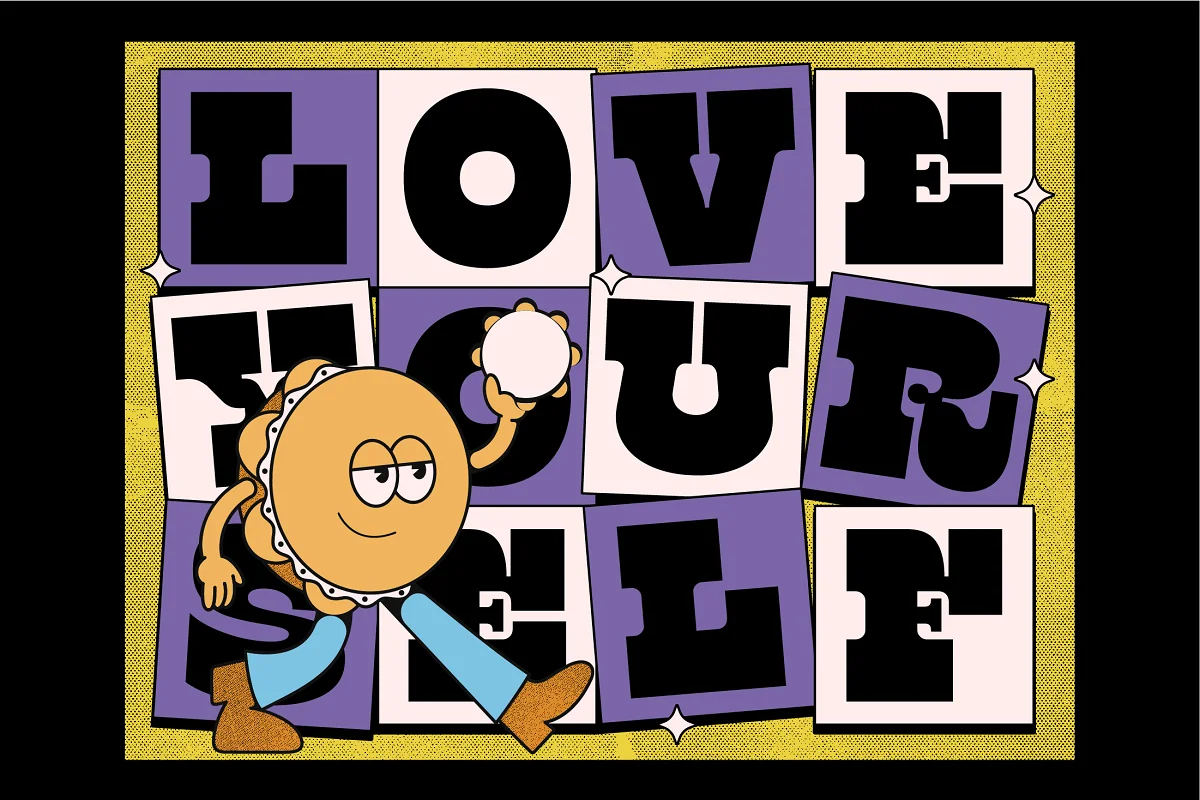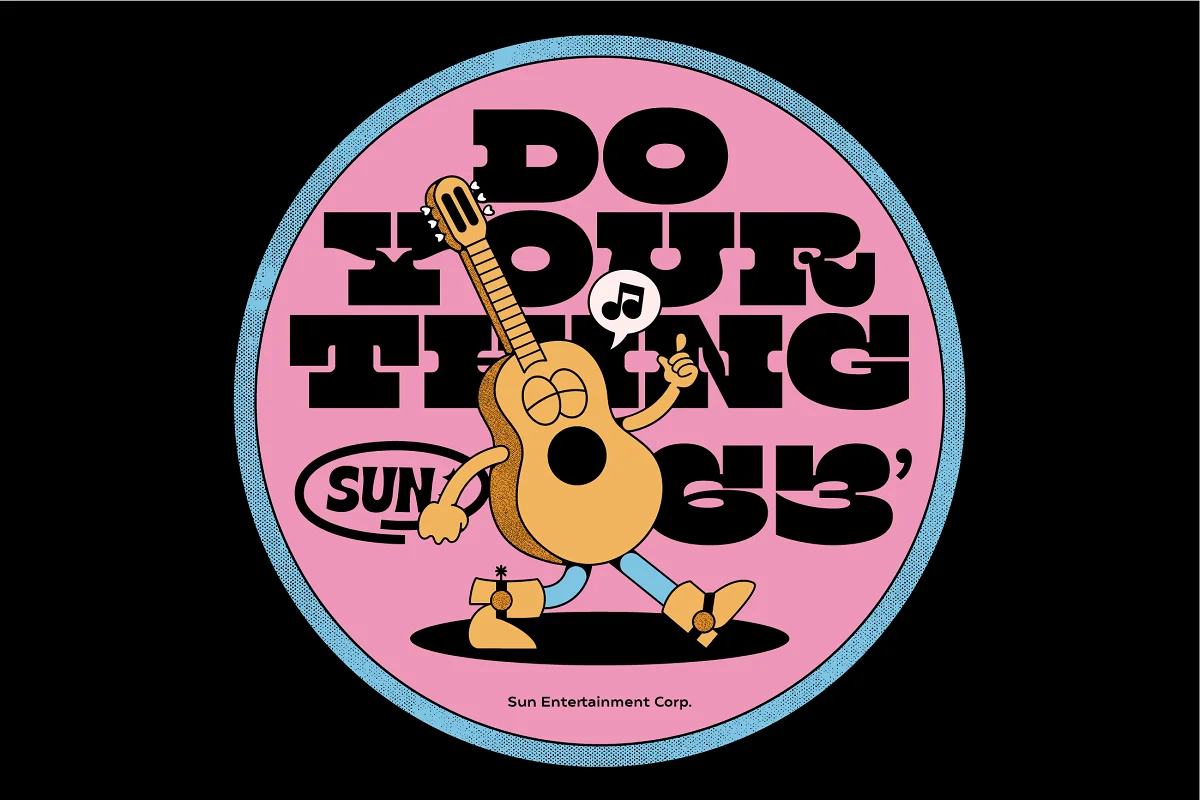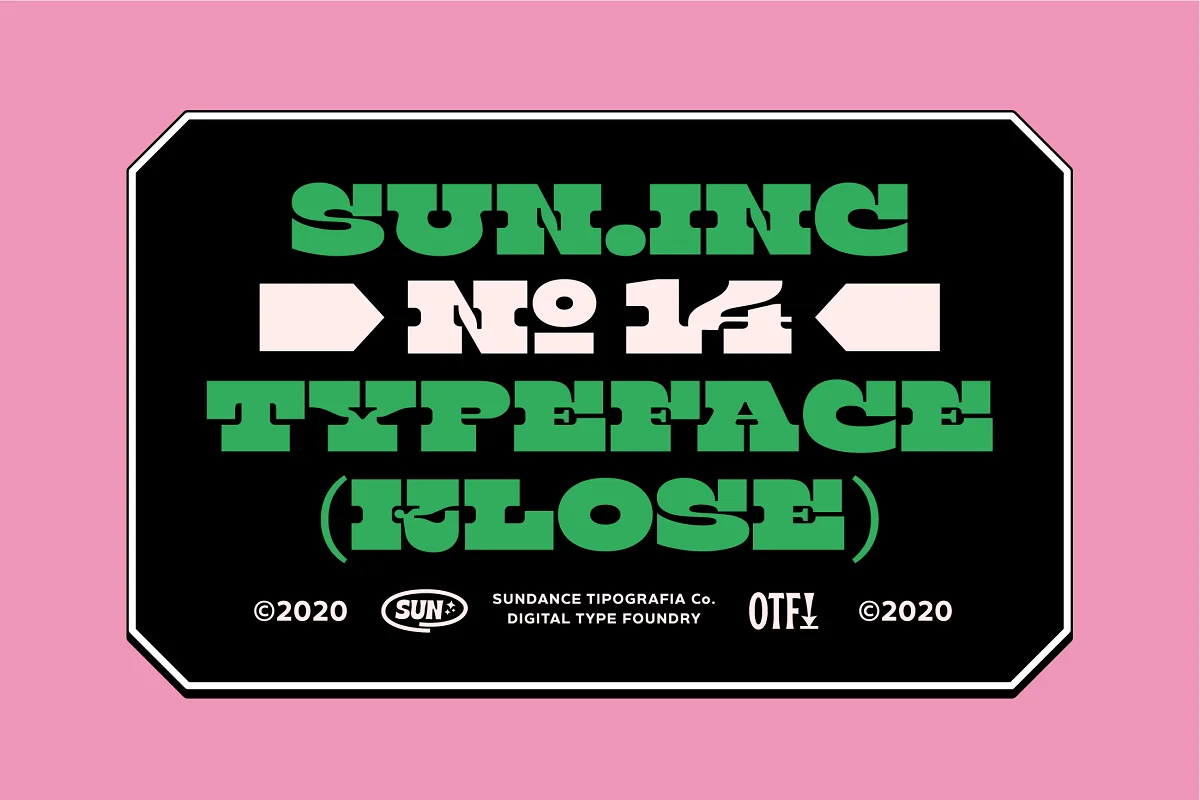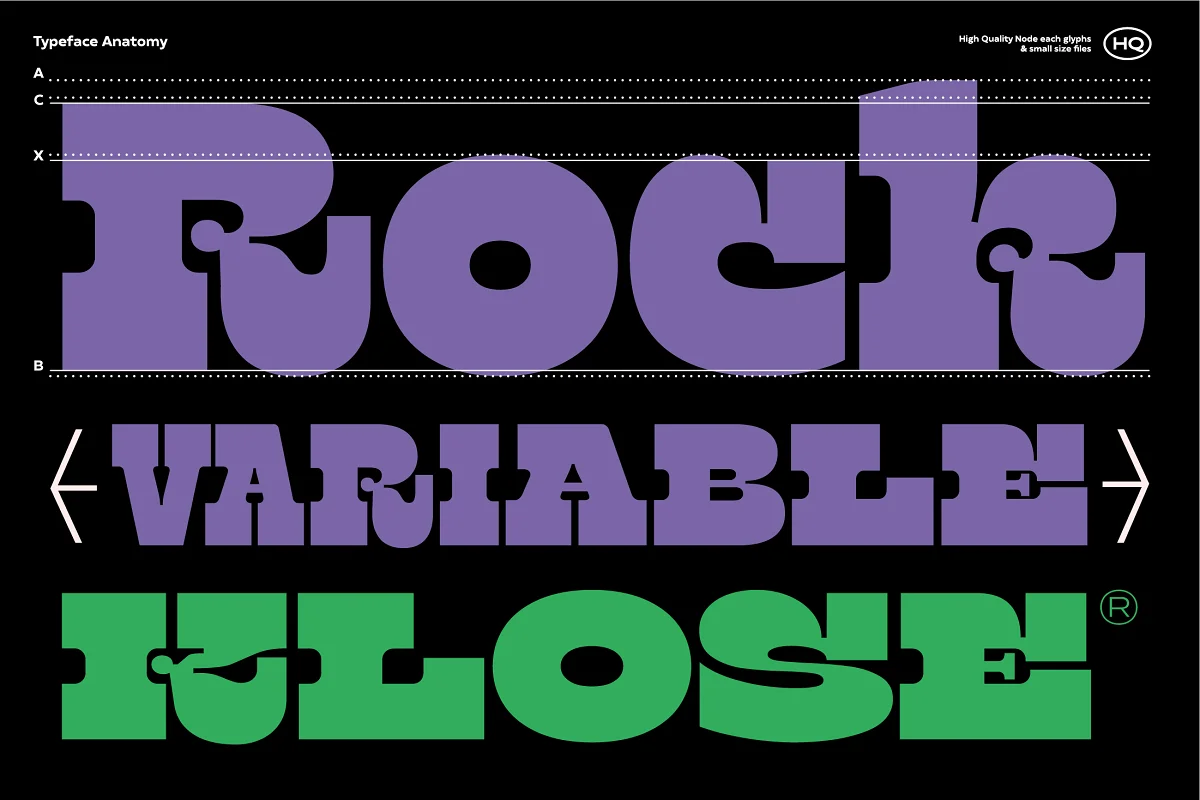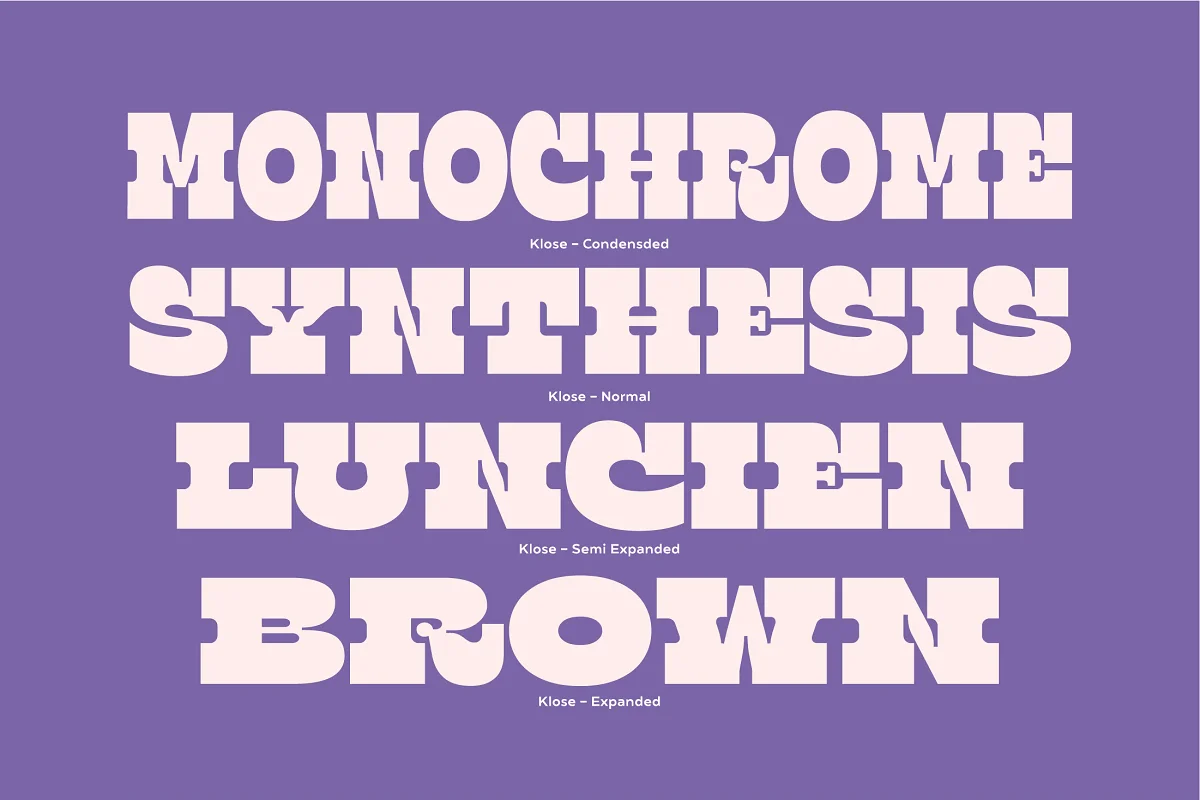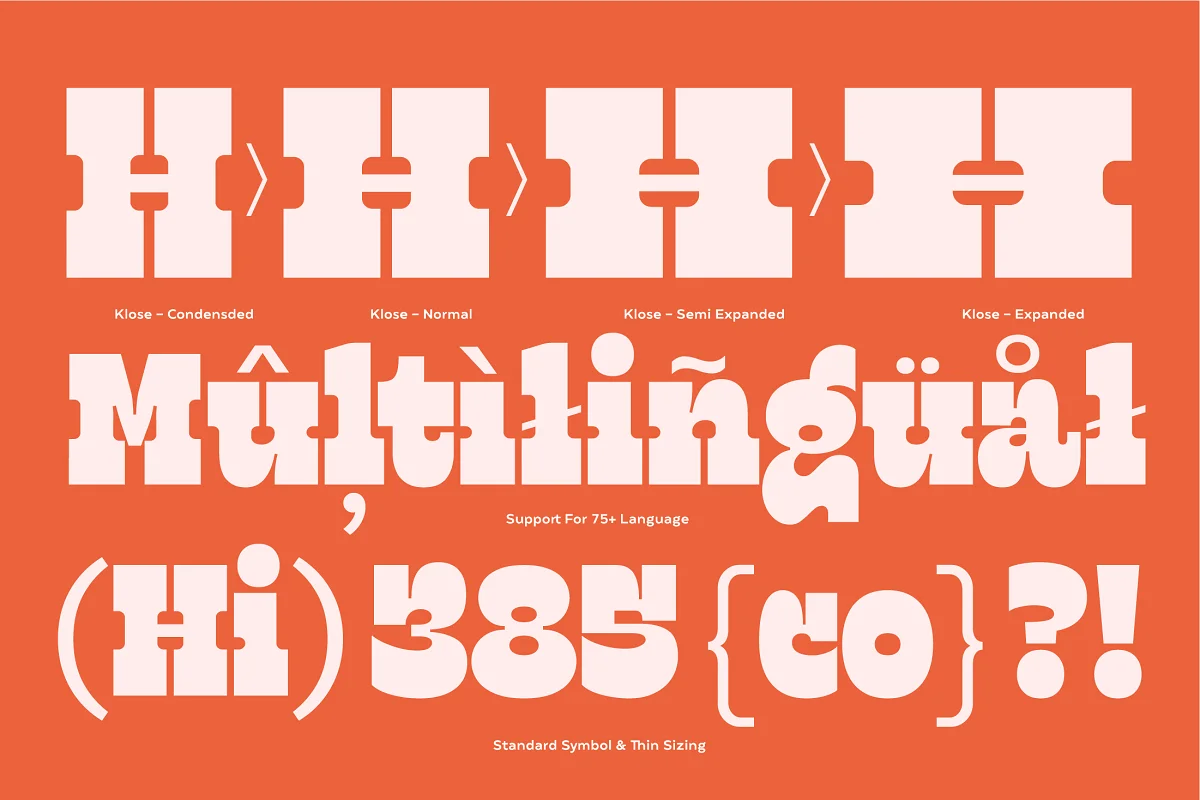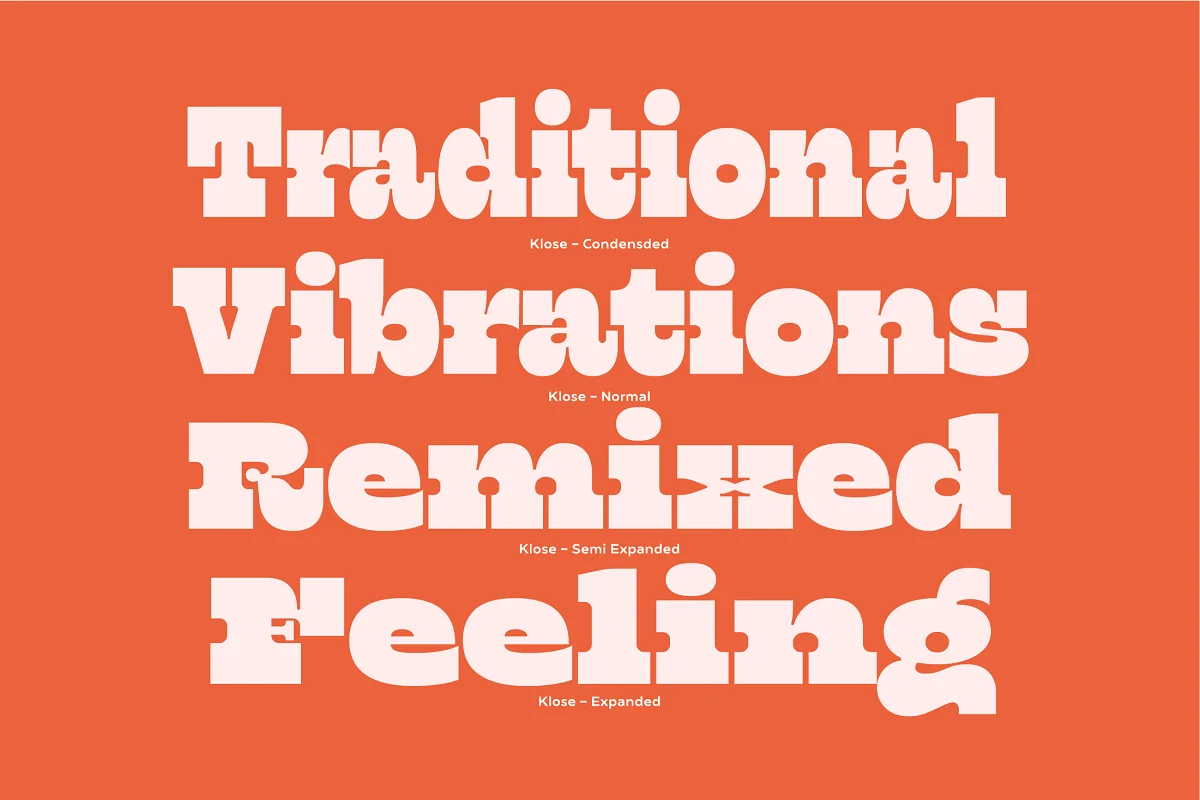
Giới thiệu Klose Slab Một kiểu chữ cổ điển khác từ Studio Sun (SUN014) cho bộ sưu tập Phông chữ của bạn. Klose có 4 kiểu (rút gọn, bình thường, bán mở rộng và mở rộng) cũng có sẵn ở định dạng Phông chữ có thể thay đổi (để tùy chỉnh độ rộng). Hoàn hảo cho logo, văn bản tiêu đề, văn bản được hiển thị và nhiều hơn nữa). Klose hỗ trợ thêm 75 ngôn ngữ (tiếng Latin pro).